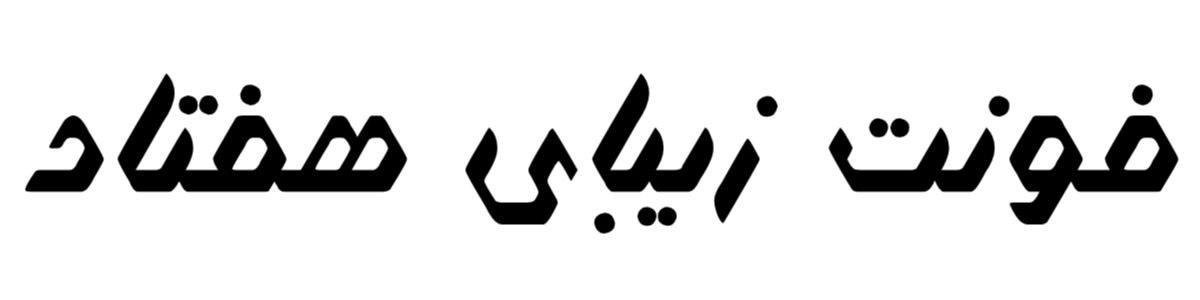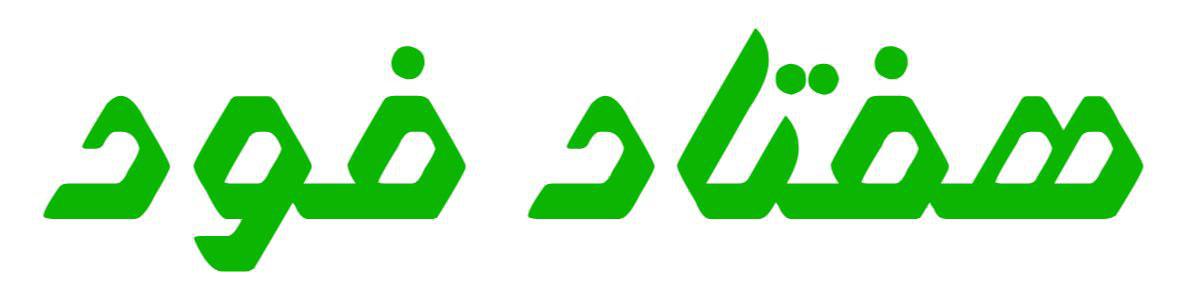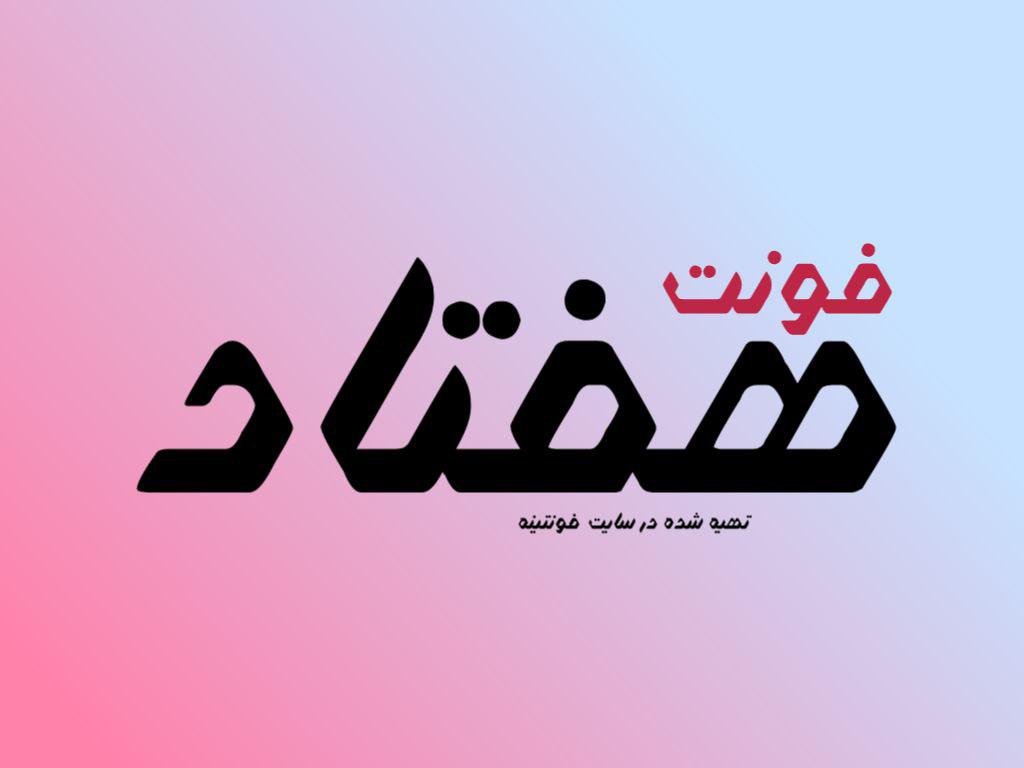
دانلود فونت هفتاد در خدمت شما بزرگورارن هستیم با ارائه فونت زیبا و فارسی هفتاد این فونت برای طراحی های لوگو و بنر و…. مورد استفاده قرار میگیرد.
ویژگی های فونت هفتاد :
• مدرن و کاربردی
• زیبا و خاص
• مناسب طراحی لوگو و بنر
تصاویری زیبا از طراحی های خاص با فونت هفتاد که برای نمایش و نمونه پیش فرضی از نمایش این فونت کاربردی طراحی شده است
فونت زیبای هفتاد
هفتاد فود